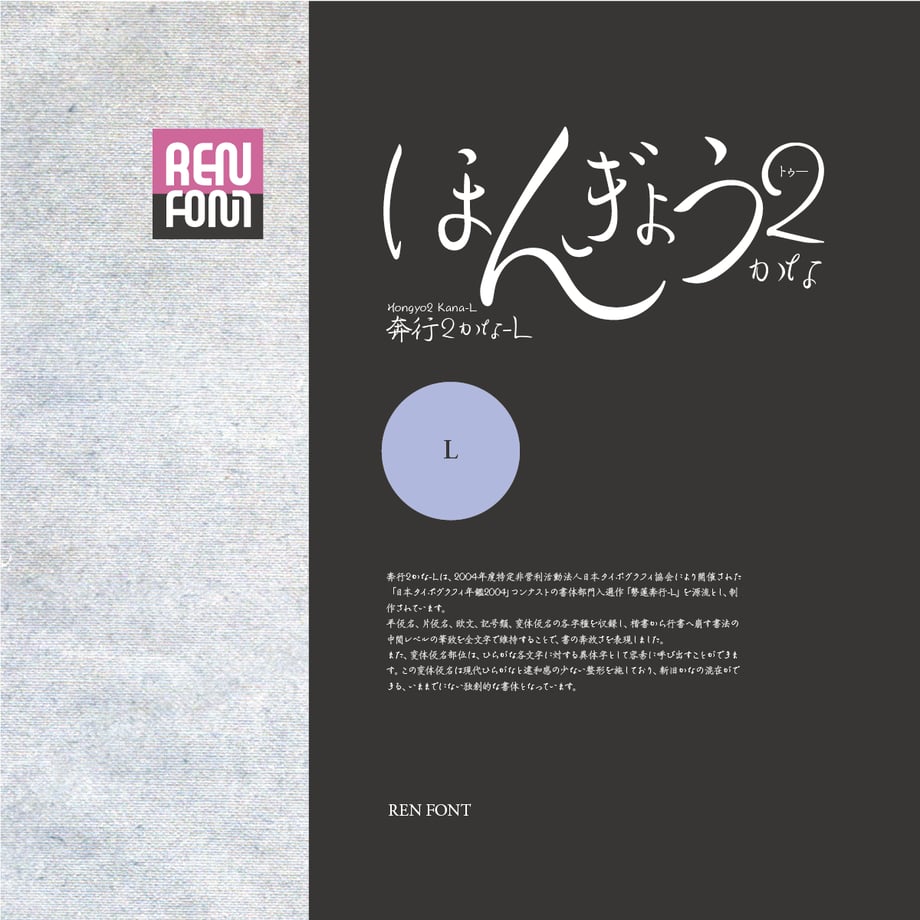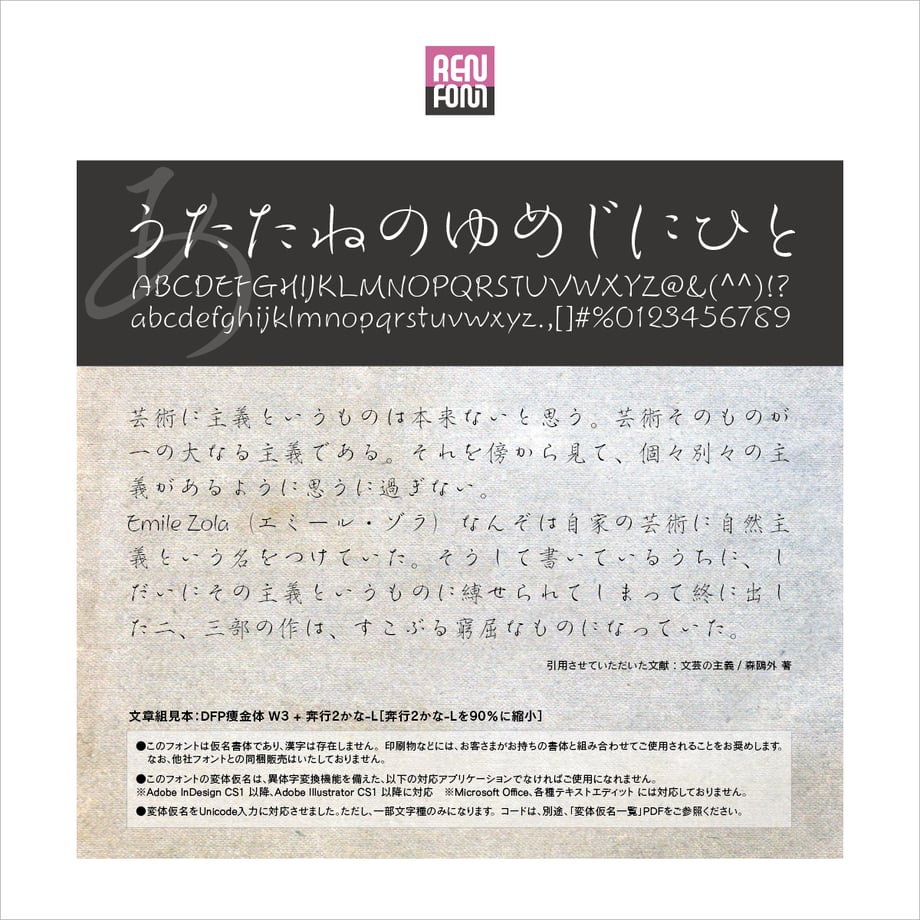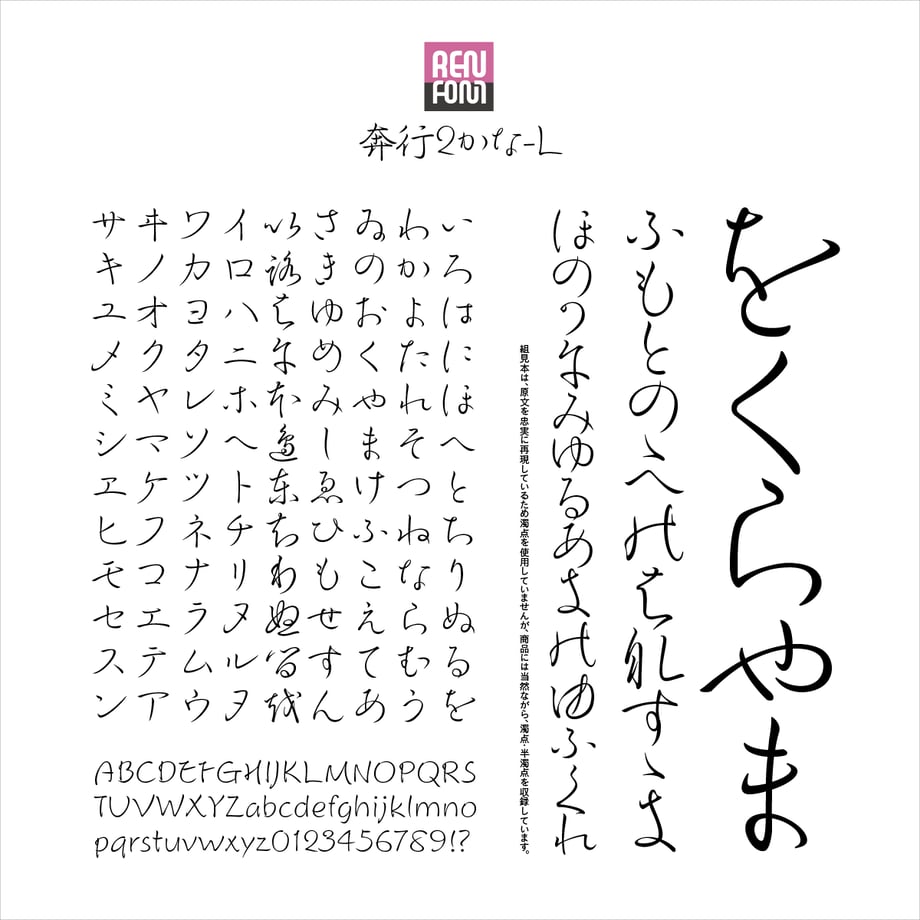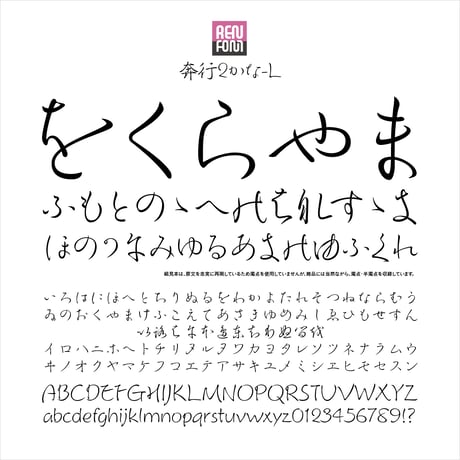
優美な仮名文字、変体仮名も収録
奔行2かな-Lは、2004年度特定非営利活動法人日本タイポグラフィ協会により開催された「日本タイポグラフィ年鑑2004」コンテストの書体部門入選作「勢蓮奔行-L」を源流とし、制作されています。
平仮名、片仮名、欧文、記号類、変体仮名の各字種を収録し、楷書から行書へ崩す書法の中間レベルの筆致を全文字で維持することで、書の奔放さを表現しました。
また、変体仮名部位は、ひらがな各文字に対する異体字として容易に呼び出すことができます。この変体仮名は現代ひらがなと違和感の少ない整形を施しており、新旧かなの混在ができる、いままでにない独創的な書体となっています。
●現代仮名
文章の実に7割を占めると言われる仮名は、文章の雰囲気を決めてしまう重要な構成要素です。奔行2かな-Lは、行書の雰囲気を持ちながら、明朝の漢字ともよくマッチし、行の流れを美しく彩ります。
●変体仮名(旧かな)
いままでは求めても得られなかった、デジタル化された変体仮名。現代仮名とあわせても違和感がありません。また、変体仮名のいのちとも言うべき筆運びは、古今さまざまな書からヒントを得て、作者の筆致を忠実に再現しました。
欧文・数字は、両仮名に合わせて独自にデザインしました。
筆文字風でありながら、欧文のセオリーを守っているので、ばらつきがなく、統一感の取れた美しい組を得られます。単独でも十分通用する完成度の高い書体に仕上がっています。
●変体仮名について
奔行2かな-Lには拗音・促音・濁音および「ん」以外の全ての各現代仮名の「音」に対応した変体仮名が320文字追加装備されております。
■収録文字 1,121 文字
・変体仮名(327文字)
・全角欧文 94文字
・常用する句読点類、約物類のみ